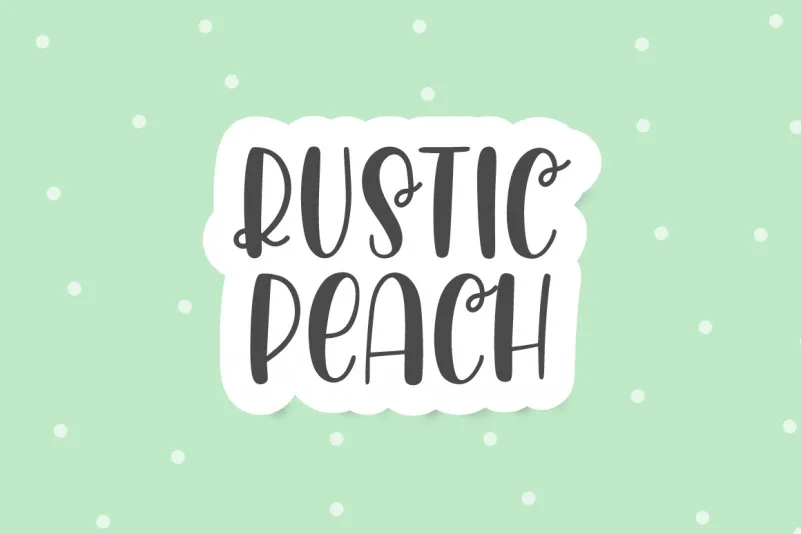
Rustic Peach Font – Download Grátis
A Rustic Peach Font é uma fonte que transmite charme natural e elegância à sua identidade visual. Essa fonte foi criada de forma a parecer escrita a mão, com detalhes leves nos cantos dos caracteres, garantindo tanto um aspecto único quanto legibilidade excelente. Ideal para ambientes onde um toque de sofisticação é necessário, como logomarcas, mensagens públicas em websites ou blogs, ilustrações SVG e artefatos impressos na etiqueta ou têxtil, a Rustic Peach se destaca não só por sua beleza visual, mas também pela facilidade de leitura. Seja para personalizar uma camiseta de esportes ou criar um site exclusivo, essa fonte atende perfeitamente aos mais variados projetos gráficos. Sem dúvida, ela é uma escolha inteligente para aqueles que desejam incorporar um toque único e refinado ao seu trabalho visual.